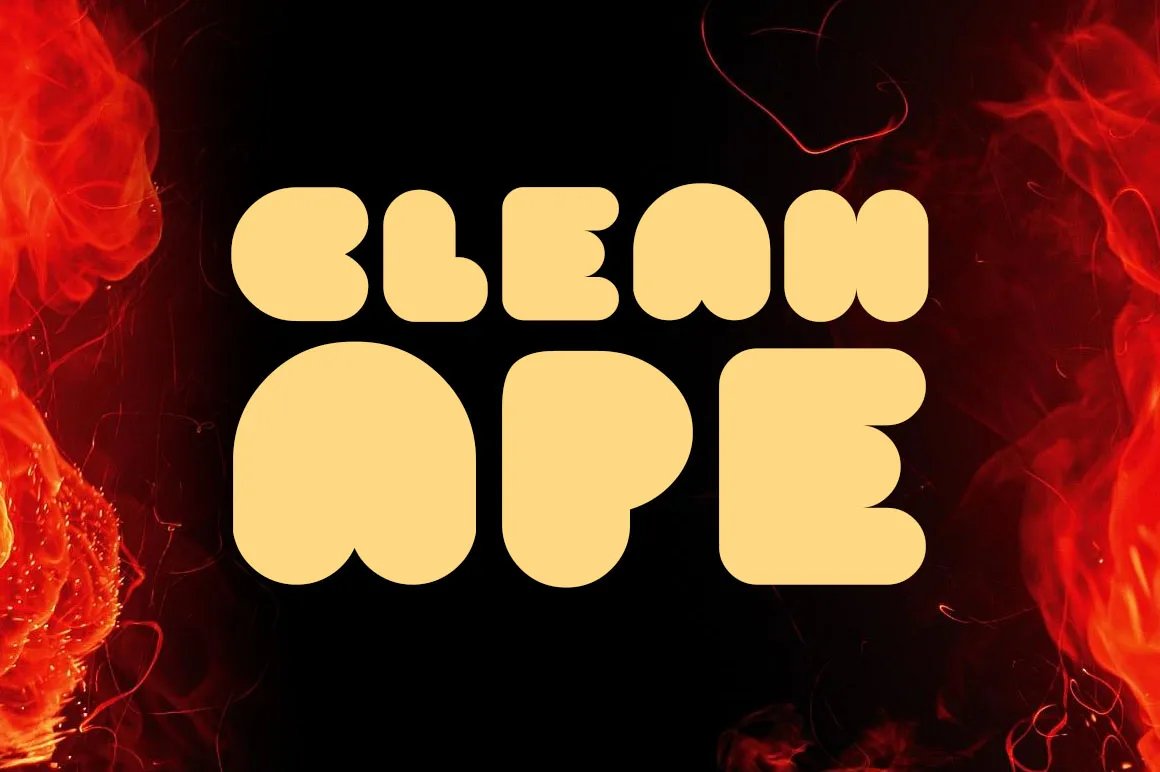
Clean Ape Typeface – Download Grátis
A Clean Ape Typeface é uma nova abordagem no mundo dos tipografias exibicionais que está trazendo uma sensação fresca para os projetos digitais e impressos. Idealmente, ela seria perfeita para um projeto de design a ser apresentado ao cliente ou público. As linhas arredondadas e o design leve do Clean Ape oferecem uma aparência suave e elegante que se destaca em qualquer layout. O designer Rahadi Istiko apresentou esta fonte como algo revolucionário, projetada para criar cabeçalhos e elementos gráficos impecáveis e vibrantes. A Clean Ape é perfeita para os entusiastas de design de todos os níveis que procuram algo diferente e criativo em suas criações. Ela pode ser usada no campo da arte impressa, como capas de livros ou até mesmo na desenvolvimento de interfaces de usuário de jogos. Suas linhas fluidas permitem um texto atraente para diversos projetos divertidos — seja um site amigável e deslumbrante ou uma interface interativa em um jogo que vai deixar os usuários impressionados com seu design elegante.